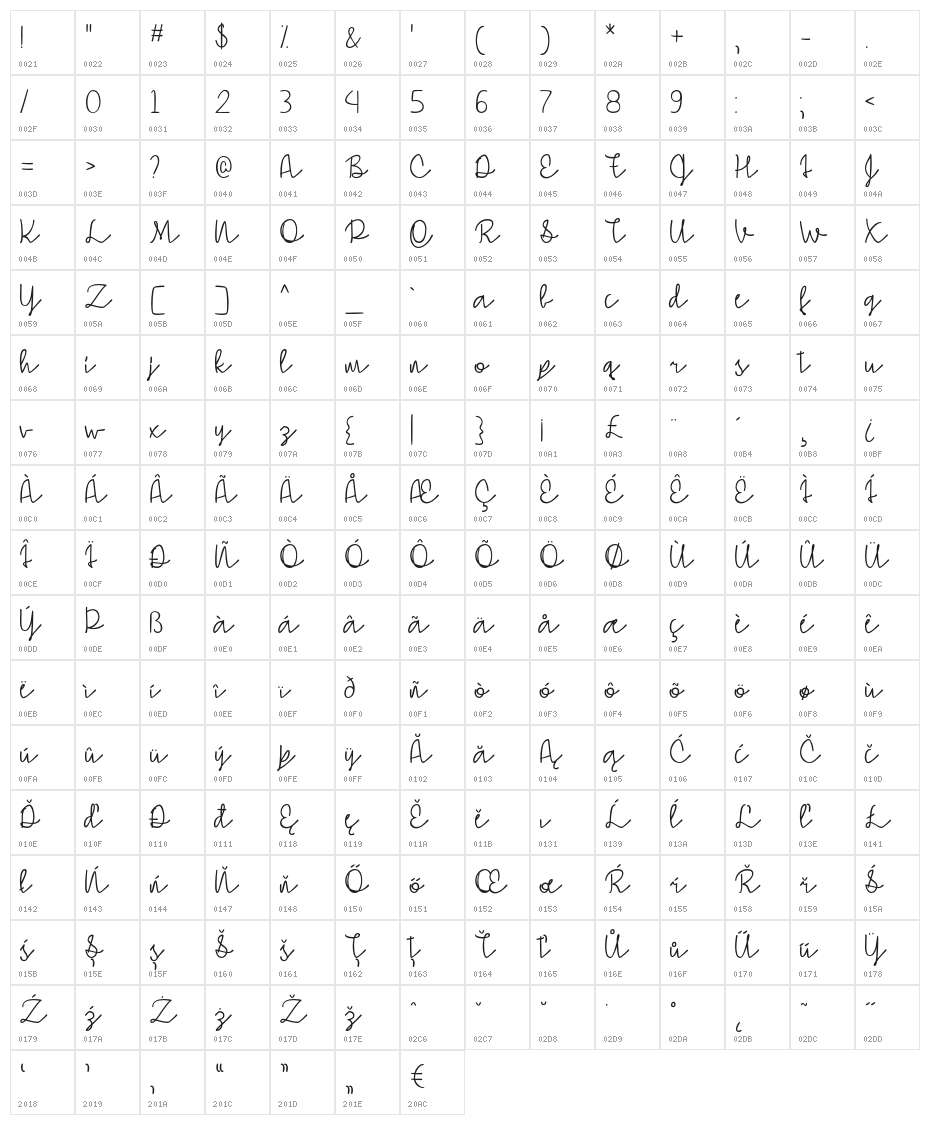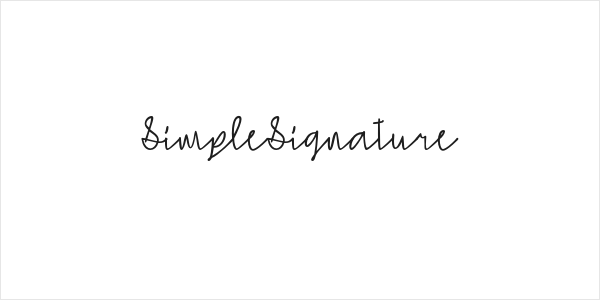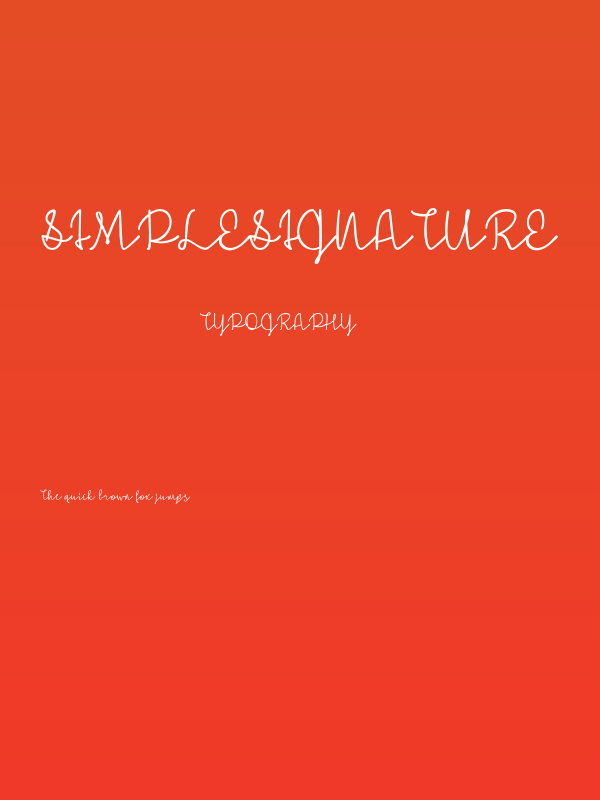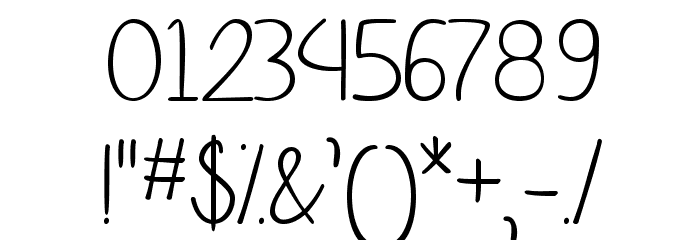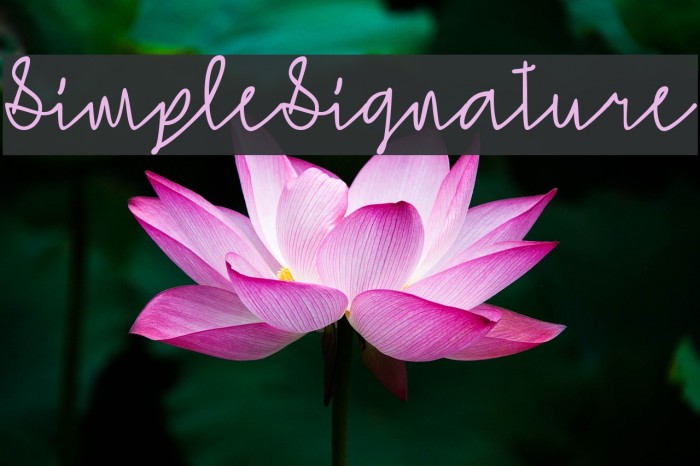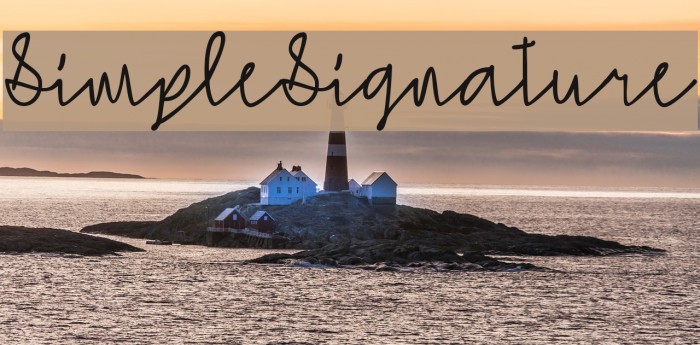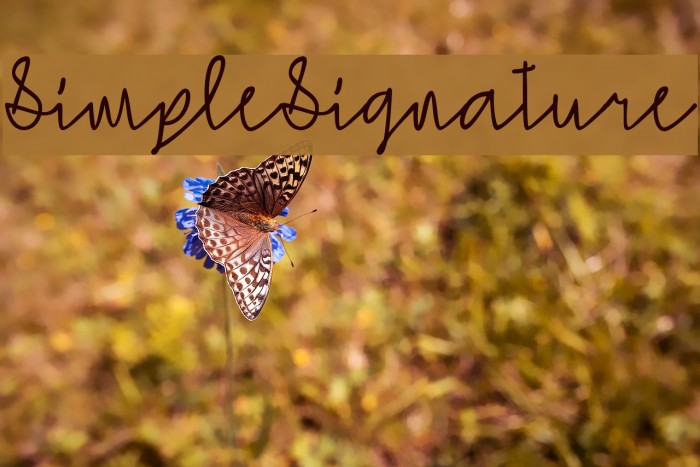
SimpleSignature Font
| Estilo general | Casual, Elegant |
| Caso de uso | Logos, Invitations, Personal Branding |
| Proyectos propuestos | Ideal for personal branding, invitations, greeting cards, and logo design. |
| Autor | Fonts by Måns Grebäck |